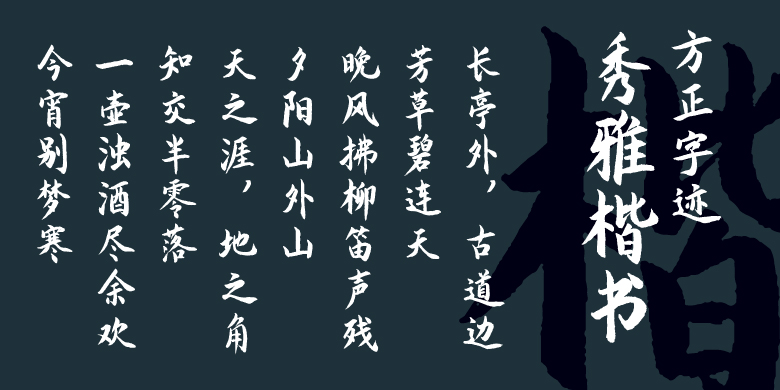
方正字迹-秀雅楷书
安景臣
常规书写·毛笔
该字体是采用仿毛笔风格秀丽笔书写的楷书字体。鉴于目前字库繁多,但好的楷书风格字体比较少的现状,设计书写了此套字体。该字体采用毛笔风格秀丽笔书写,使字体既有毛笔的古朴端庄,又有现代风格的秀丽典雅,实用性与艺术性兼备,可用于仿古籍排版、影视字幕、商品包装、商标标志、广告语宣传、网络宣传、书籍出版等场景。